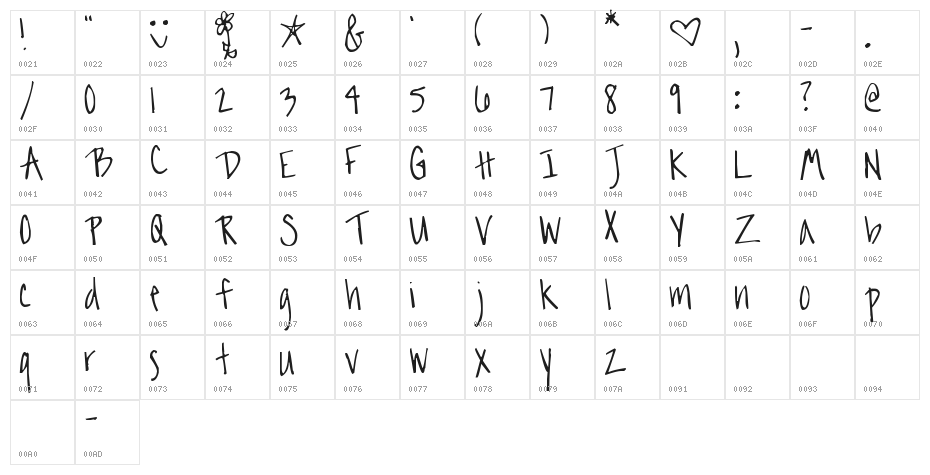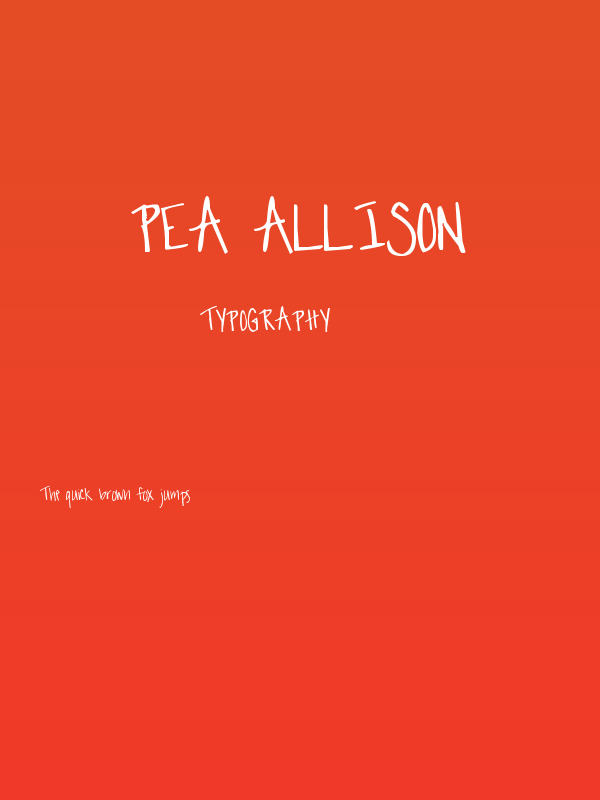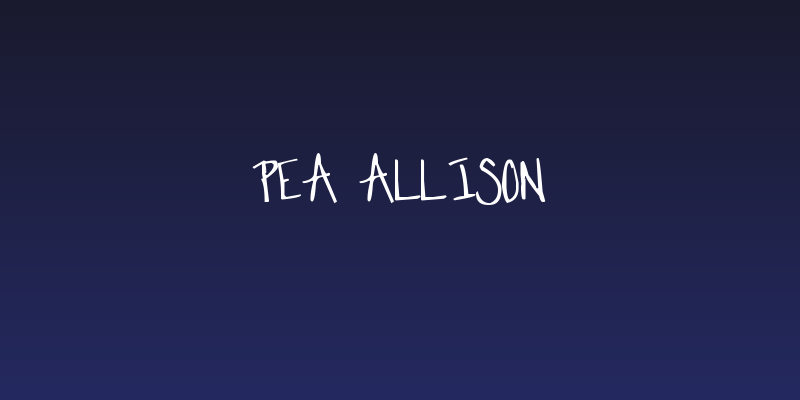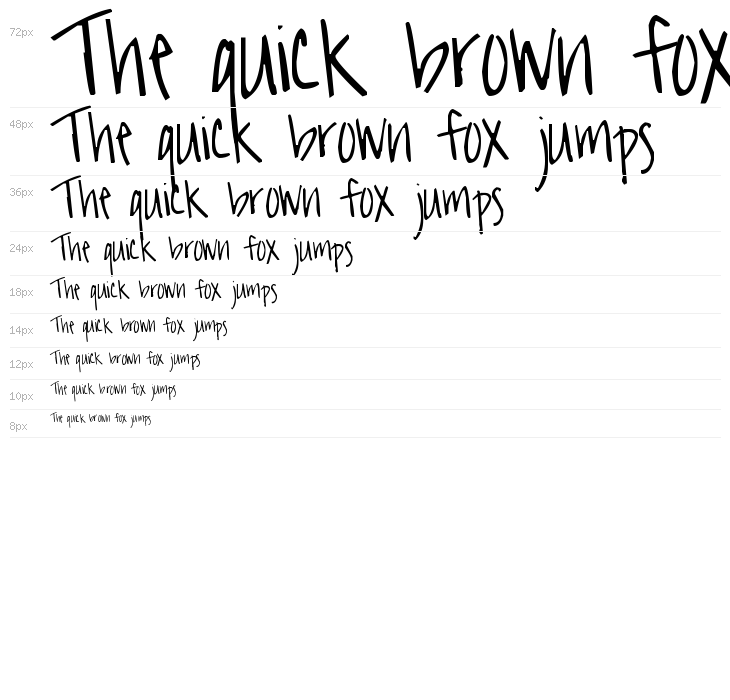
Pea Allison Font
| Stile generale | Casual, Playful |
| Caso d'uso | Logos, Headlines, Informal Text |
| Progetti proposti | Ideal for greeting cards, personal notes, children's books, and creative branding projects. |